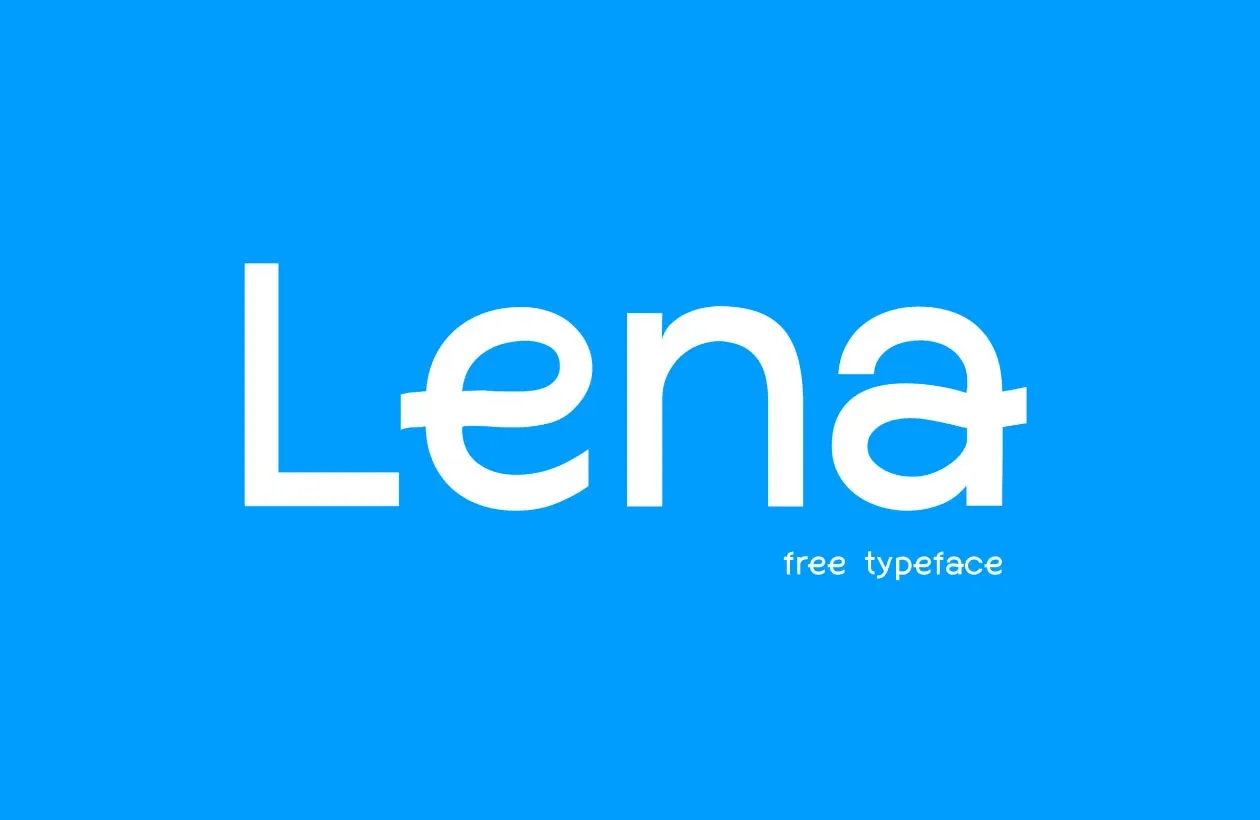
A Lena Font é uma tipografia sans serif meticulosa projetada por Vsevolod Abramov. Suas linhas leves e retangulares permitem que ela seja usada em um vasto range de situações, desde design para web até arte coletiva, passando por criação de logotipos e tipografia para casamentos e designs modernos e tecnológicos. Esta fonte é perfeitamente adaptável a diversas necessidades de design visual, tornando-a uma escolha versátil para qualquer projeto que exija um estilo simples e contemporâneo. Com Lena em sua carteira de recursos, designers podem criar design para mídias sociais e conteúdo visuais, adicionar um toque moderno aos websites e interfaces de usuário, e transformar ambientes publicitários com sua arte coletiva e identidade visual. Ainda mais significativo é o seu uso na criação de logotipos e marcas, bem como para a tipografia no design das casamentos, todas estas situações que exigem um toque único e moderno.